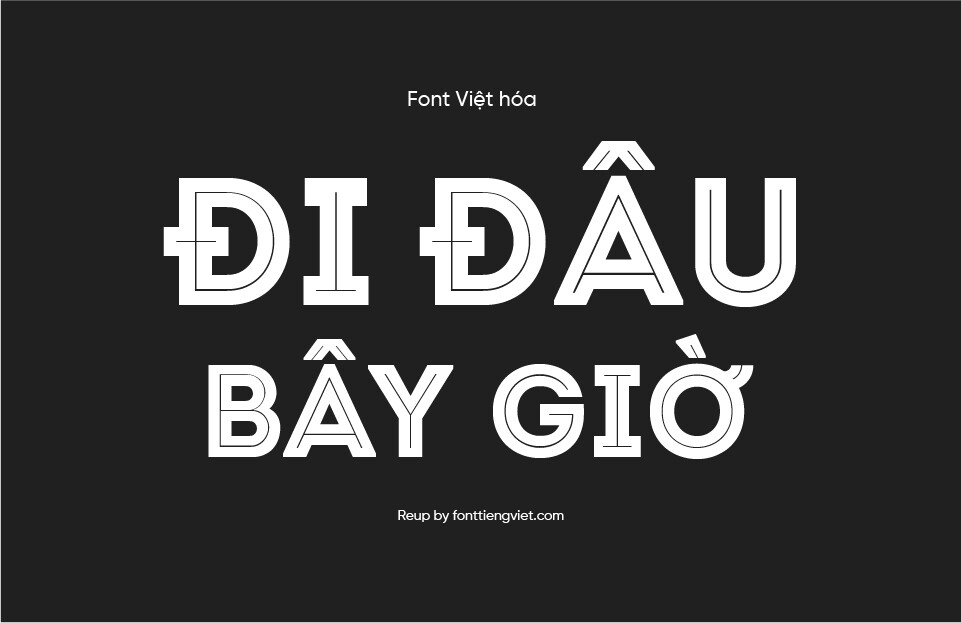
Font Việt hóa Intro Inline
Giới thiệu về Font Việt hóa Intro Inline
Trong thế giới thiết kế đồ họa, việc lựa chọn một Font Miễn Phí chất lượng luôn là ưu tiên hàng đầu của các bạn học sinh và giáo viên. Font Việt hóa Intro Inline nổi lên như một hiện tượng nhờ cấu trúc hình học chuẩn mực và phong cách hiện đại. Đây là phiên bản đặc biệt trong bộ font Intro nổi tiếng, được tinh chỉnh để phù hợp hoàn hảo với bảng mã tiếng Việt. Với những đường nét mảnh mai lồng ghép bên trong các ký tự dày dặn, font chữ này tạo ra hiệu ứng thị giác phân tầng cực kỳ ấn tượng và chuyên nghiệp cho mọi bản thiết kế.
Tại sao nên dùng Font Việt hóa Intro Inline cho học tập?
Font Việt hóa Intro Inline sở hữu khả năng hiển thị tuyệt vời trên cả màn hình điện tử và bản in. Trong môi trường học đường, các bạn có thể dùng font này để làm tiêu đề báo tường, thiết kế bìa tiểu luận hoặc sáng tạo các slide bài giảng sinh động. Sự kết hợp giữa nét chữ đậm và đường line chạy dọc giúp nội dung trở nên nổi bật nhưng vẫn giữ được sự tinh tế, không gây rối mắt cho người xem.
Cách ứng dụng Font Việt hóa Intro Inline hiệu quả
Để khai thác tối đa vẻ đẹp của Font Việt hóa Intro Inline, bạn nên kết hợp nó với các font chữ không chân (sans-serif) đơn giản ở phần nội dung. Kiểu chữ này cực kỳ phù hợp cho các tiêu đề lớn, logo hoặc các câu trích dẫn truyền cảm hứng trên mạng xã hội. Nhờ tính linh hoạt, bạn có thể áp dụng vào nhiều chủ đề từ công nghệ, thể thao cho đến nghệ thuật đương đại.
Khi sử dụng Font Việt hóa Intro Inline, hãy chú ý đến khoảng cách giữa các chữ cái (kerning) để đảm bảo tính thẩm mỹ cao nhất. Font chữ này hoạt động tốt nhất ở kích thước lớn, giúp các chi tiết inline bên trong hiện rõ nét và thu hút.